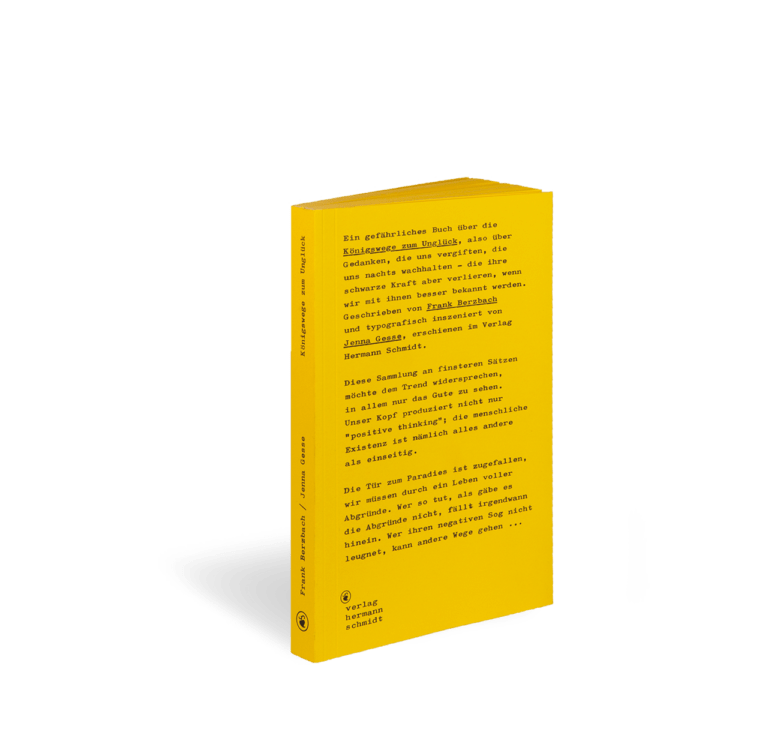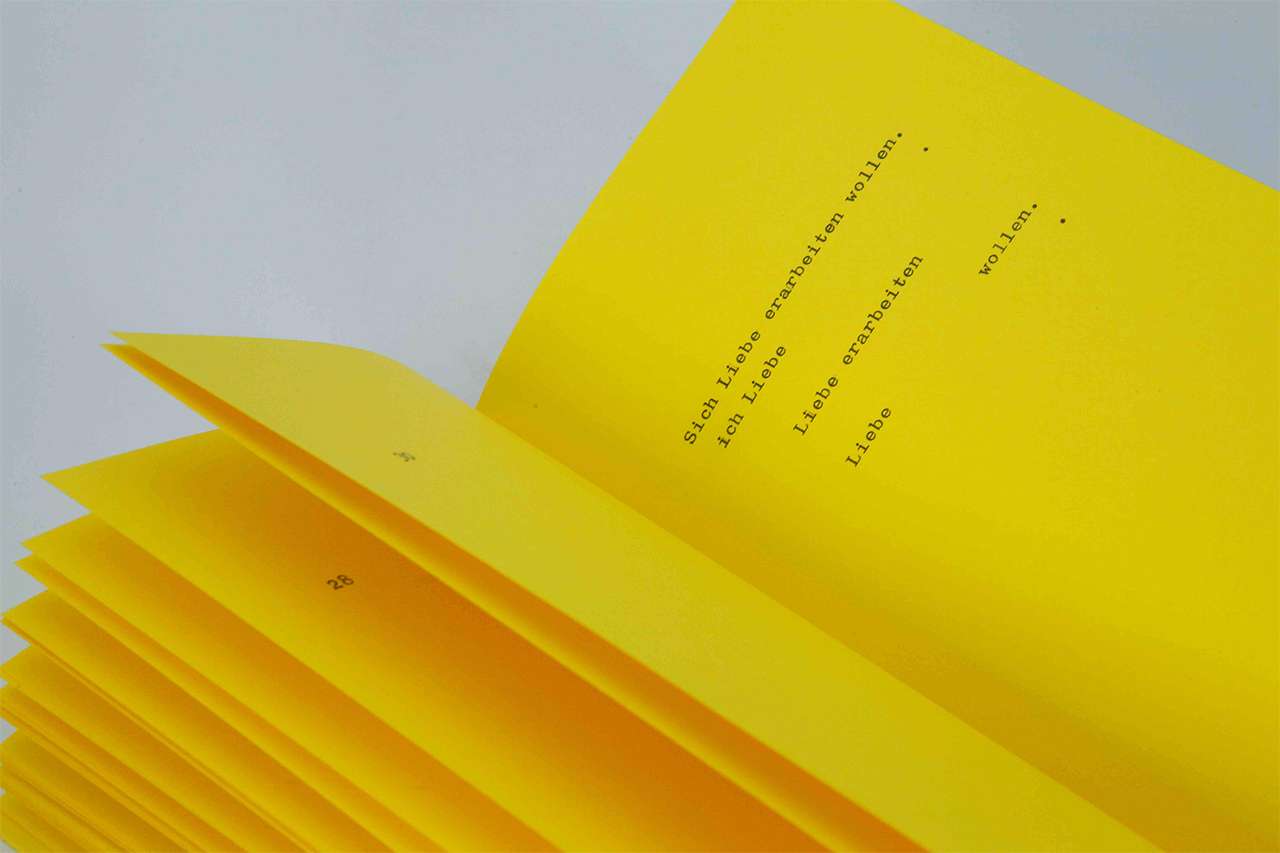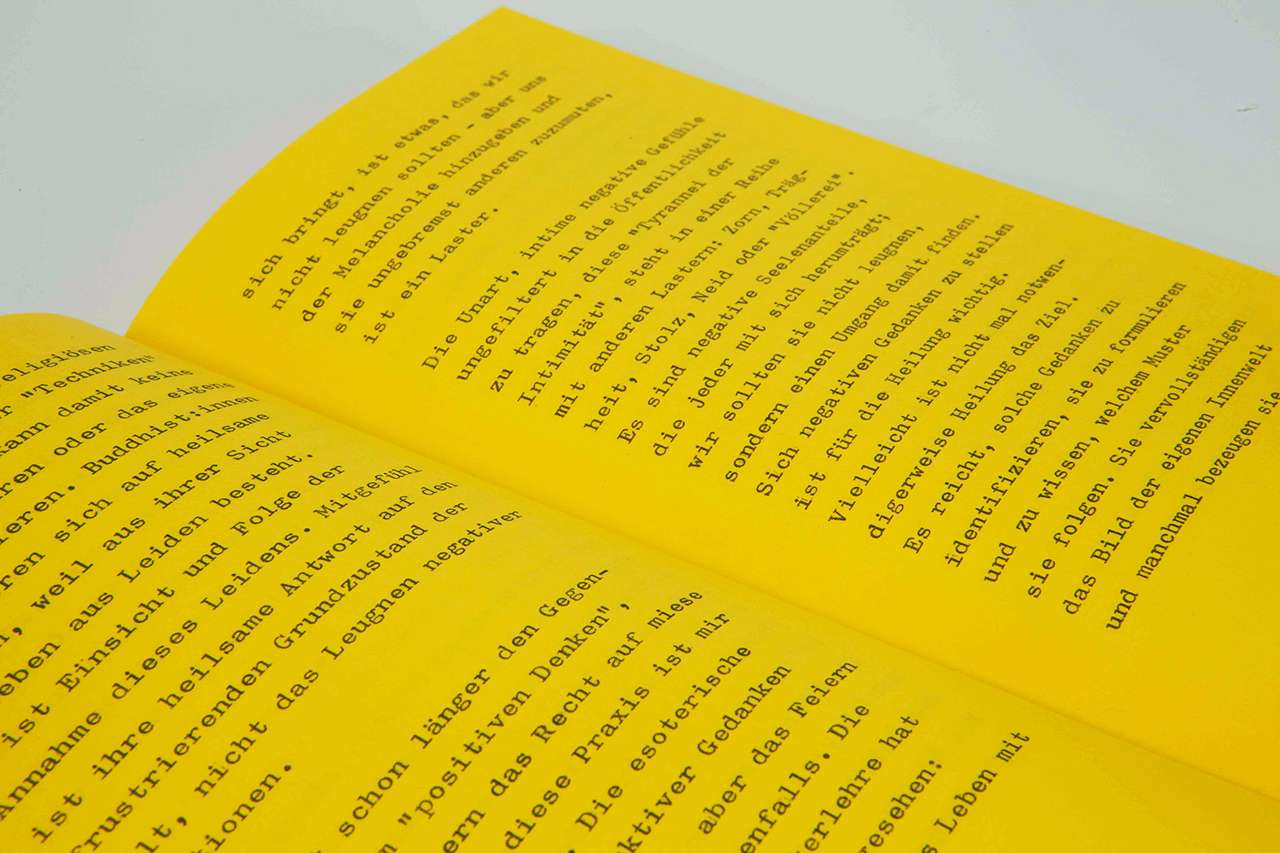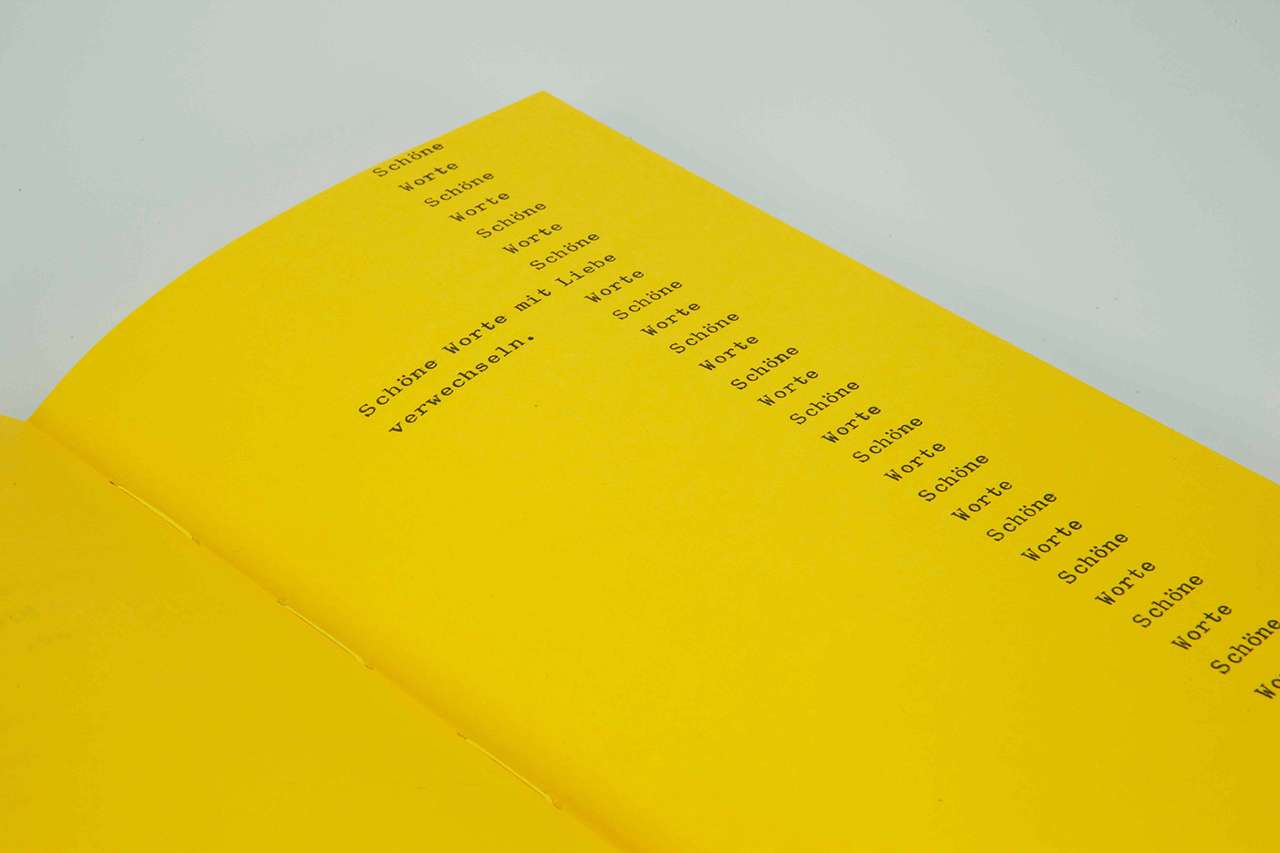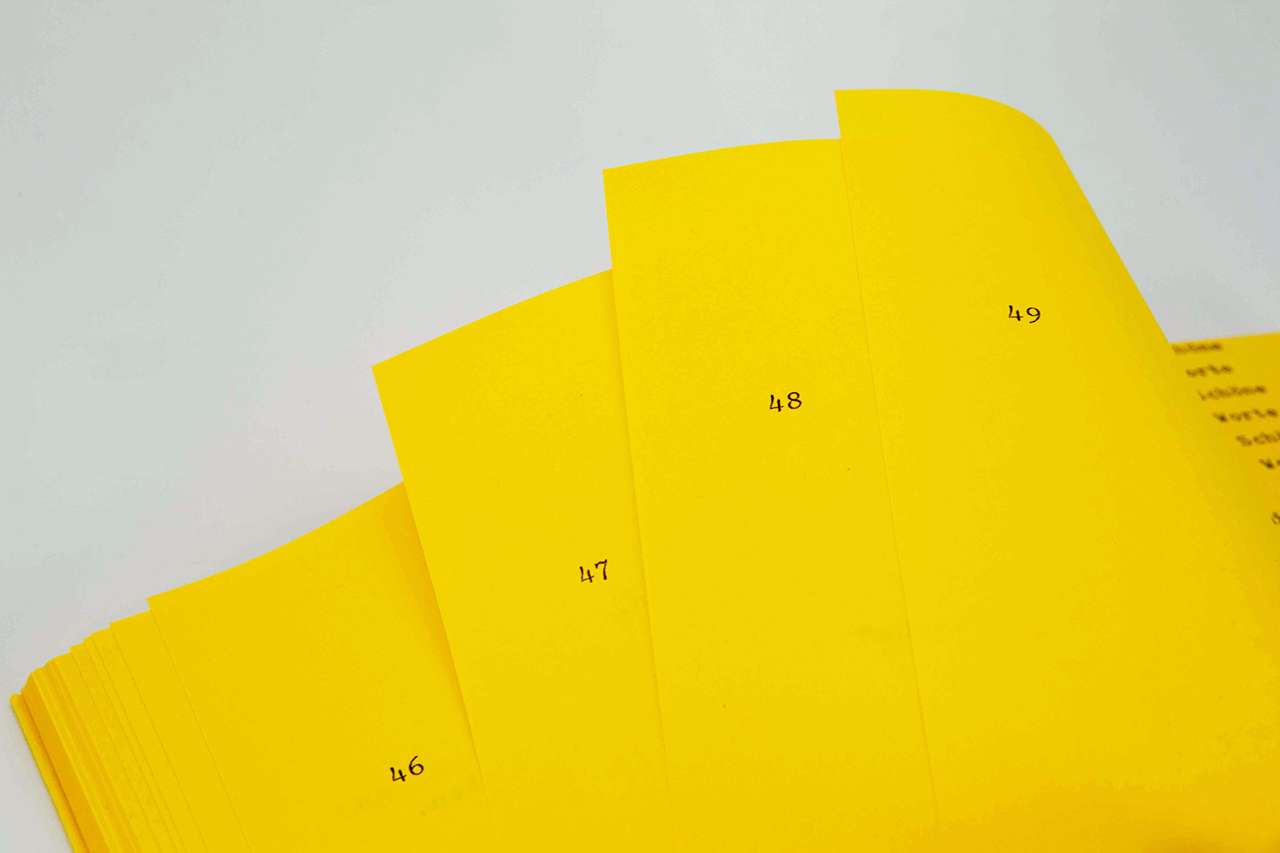
Destruktive Denkmuster erkennen
Kennen Sie das? Sie liegen nachts wach und giftige Gedanken ergreifen von Ihnen Besitz. Lassen sich nicht verscheuchen. Werden immer mächtiger, während auf Instagram doch alle um die Wette lächeln. Während die Regale mit Glücksratgebern und positiver Psychologie überquellen und eine ganze Glücksindustrie boomt. Während es das Leben mit allen um Sie herum doch gut meint.
Über diese Nächte spricht man nicht. Über die Sätze, die dem Selbstbewusstsein empfindlich zusetzen, auch nicht. Das passt nicht in eine Welt, die good vibes only verlangt. In der aus der Pursuit of Happiness längst ein Zwang zum Glücklichsein geworden ist. Selbst schuld, wer seinen Weg zum Glück nicht findet. Hat nicht hart genug daran gearbeitet. Und versteckt sich besser.
Und dann entdecken Sie ein Buch mit 100 Königswegen zum Unglück.
Sie erkennen, dass Sie nicht allein sind mit dem einen oder anderen destruktiven Denkmuster. Dass auch in anderen Köpfen Sätze wohnen, die sich unbarmherzig Bahn brechen. Dass wir nicht entscheiden, was wir denken. Dass negative Gedanken kommen, ob wir wollen oder nicht. Dass sie zum Leben gehören. Diese Erkenntnis hilft schon ungemein, aber dieses Buch kann mehr.
Indem Frank Berzbach seine 100 Wege zum Unglück teilt, hilft er Ihnen, Ihre giftigen Gedanken zu erkennen. Sie ans Licht zu zerren. Abstand zu gewinnen. Zu entscheiden, wie Sie mit ihnen umgehen. Und ihnen damit einen Teil ihrer zerstörerischen Macht zu nehmen.
»In Ihrem Kopf entstehen schlimme, negative Sätze, in meinem auch, aber das ist noch kein Unglück. Zum Königsweg ins Unglück werden sie erst, wenn wir sie glauben, uns ihnen hingeben, den Gedanken in unserem Kopf mit der Realität außerhalb verwechseln.«
Wenn Ihr Kopf dann das nächste Mal den Weg ins Unglück einschlägt, schauen Sie sich kurz um, aber gehen Sie nicht weiter.
Zu Gestaltung und Ausstattung
Dieses Buch ist ein Gemeinschaftswerk. Frank Berzbach hat es geschrieben, Jenna Gesse setzt die Königswege zum Unglück typografisch in Szene. Sie tut das mit einer alten Schreibmaschine Typ Tippa S aus der Zeit um 1975.
Königswege zum Unglück
Ein gefährliches Buch
von Hand getippt mit einer alten Tippa-Schreibmaschine